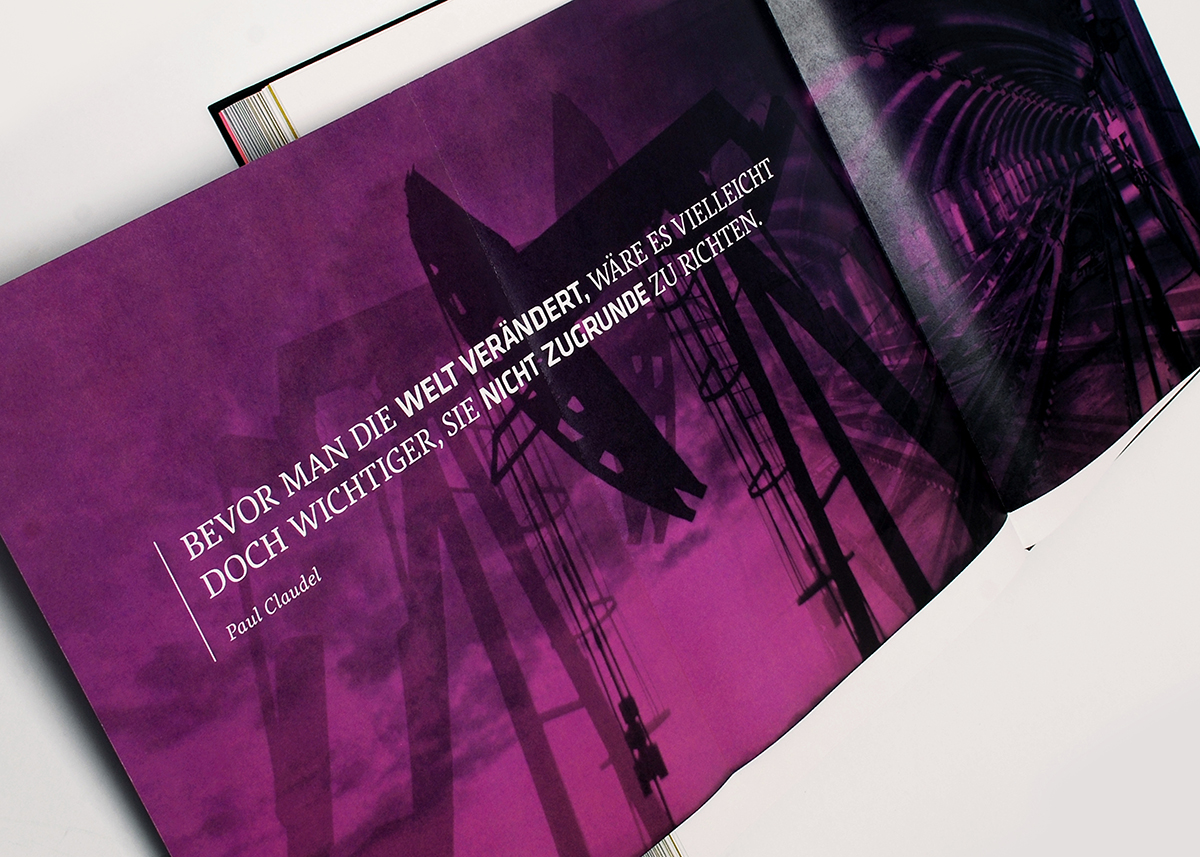
Serife passend zu Klavika
Ich bin auf der Suche nach einer schönen/modernen Serife für den Fliesstext passend zur Klavika.
Any ideas?
Die Agendatype ist echt sehr schick. Auch in der Kombination …